싸인의 느낌은 어떤 필기체를 사용하느냐에 따라 완전히 달라질 수 있어요! 같은 이름이라도 필기체를 바꾸면 분위기가 달라지고, 개성도 더욱 돋보일 수 있죠. 🖋️
예를 들어, 고전적인 필기체는 우아한 느낌을, 모던한 필기체는 세련된 분위기를, 예술적인 필기체는 독창적인 개성을 강조할 수 있어요. 🎨
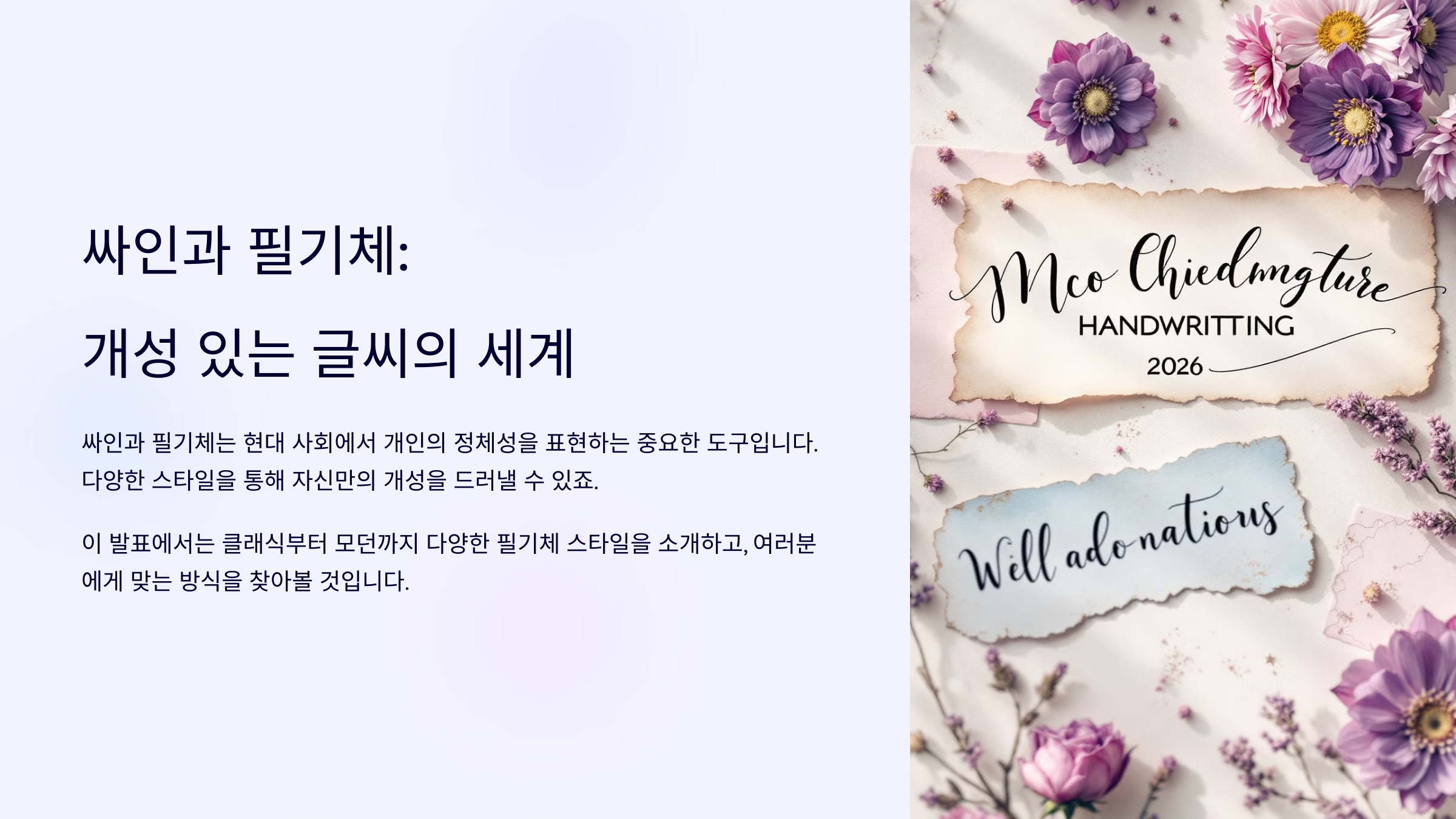
그렇다면, 싸인을 멋지게 보이게 하는 필기체에는 어떤 것들이 있을까요? 먼저, 싸인과 필기체의 관계부터 살펴볼게요! 🔍
싸인과 필기체의 관계 🖋️
싸인은 단순한 서명이 아니라 자신의 개성을 표현하는 중요한 요소예요. 특히 어떤 필기체를 선택하느냐에 따라 싸인의 느낌이 크게 달라질 수 있어요. ✍️
예를 들어, 곡선이 많고 부드러운 필기체는 우아하고 감성적인 느낌을 주고, 직선적이고 강한 필기체는 자신감과 카리스마를 강조할 수 있어요. 이처럼 필기체 하나로 싸인의 분위기가 완전히 달라질 수 있어요. 💡
📌 필기체 스타일별 싸인의 차이 🔍
필기체 스타일 특징 추천 대상 클래식한 필기체 우아하고 전통적인 느낌을 강조 고급스러운 이미지가 필요한 사람 모던한 필기체 깔끔하고 세련된 분위기 연출 비즈니스 및 공식 문서용 예술적인 필기체 곡선과 장식이 많아 독창적인 느낌 개성을 강조하고 싶은 사람 미니멀한 필기체 불필요한 요소를 제거한 심플한 스타일 깔끔한 서명을 원하는 사람 싸인 스타일을 정할 때는 자신의 이미지와 목적에 맞는 필기체를 선택하는 것이 중요해요. 그럼 먼저, 우아하고 고급스러운 클래식한 필기체 추천을 살펴볼까요? 🎩
클래식한 필기체 추천 🎩
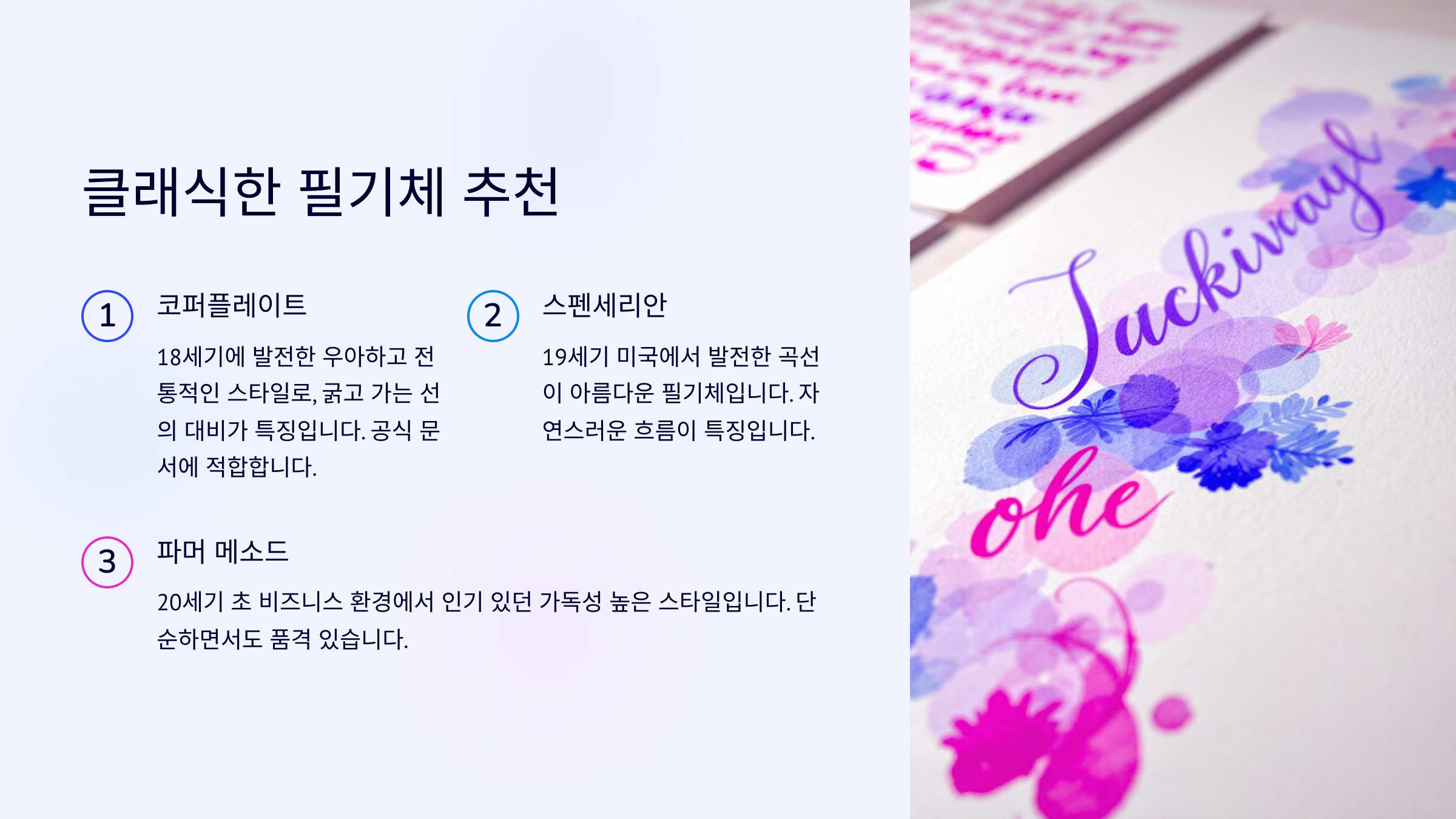
클래식한 필기체는 우아하고 고급스러운 분위기를 연출하는 데 적합해요. 특히 전통적인 싸인 스타일을 선호하는 분들에게 잘 어울려요. ✍️
고전적인 필기체는 곡선이 많고, 부드러우면서도 흐름이 자연스러운 것이 특징이에요. 예를 들어, 왕실 문서나 유명 예술가들의 서명에서 이런 스타일을 자주 볼 수 있죠. 💡
📌 클래식한 필기체 추천 ✅
필기체 특징 추천 대상 Spencerian Script 19세기 미국에서 유행한 우아한 필기체 전통적인 느낌을 원하는 분 Copperplate 곡선과 장식이 많아 귀족적인 분위기 우아한 싸인을 원한다면 Roundhand 유럽에서 발전한 부드러운 필기체 클래식하면서도 실용적인 싸인을 원할 때 Zanerian Script 예술적인 요소가 강한 고전 서체 고급스러운 스타일을 원할 때 클래식한 필기체는 전통적인 느낌과 우아함을 강조하는 데 최고예요! 그럼 이제 현대적이고 세련된 느낌을 주는 모던한 필기체도 살펴볼까요? ✨
모던하고 세련된 필기체 ✨
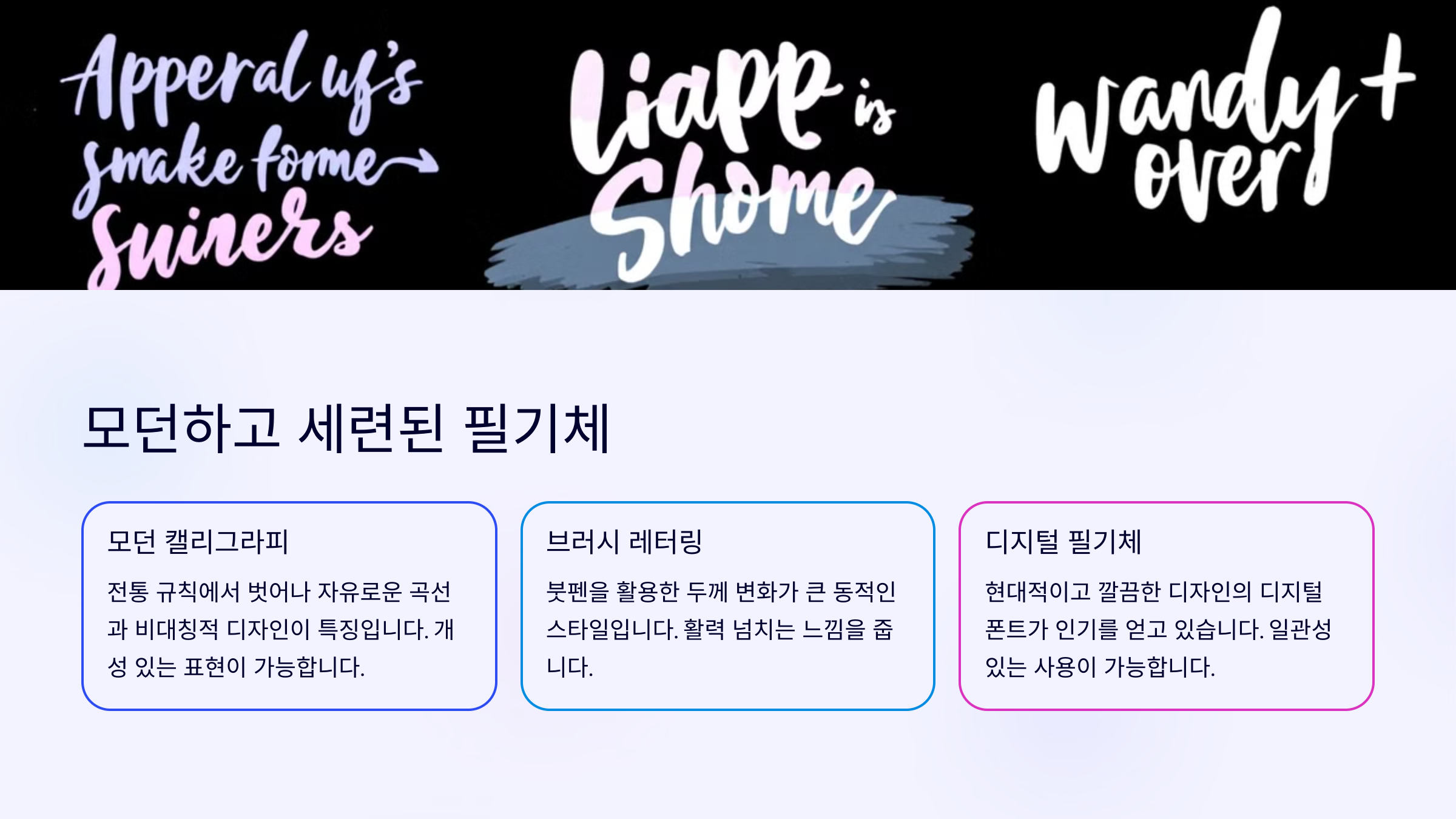
모던한 필기체는 깔끔하면서도 세련된 분위기를 연출하는 스타일이에요. 특히 비즈니스 서명, 공식 문서, 현대적인 감각의 싸인을 원할 때 적합해요. 🖋️
이런 스타일의 필기체는 획이 정리되어 있고, 불필요한 장식이 적으며, 가독성이 좋은 것이 특징이에요. 특히 CEO나 전문가들이 깔끔하고 믿음직한 이미지를 위해 선호하는 스타일이기도 해요. 💼
📌 모던한 필기체 추천 ✅
필기체 특징 추천 대상 Helvetica Script 단순하면서도 현대적인 필기체 비즈니스 및 전문직 종사자 Futura Handwritten 기하학적인 요소가 가미된 모던한 스타일 스타일리시한 싸인을 원하는 분 Monoline Script 균일한 굵기의 세련된 필기체 간결하면서도 감각적인 서명을 원할 때 Gotham Handwritten 깨끗하고 정돈된 느낌을 주는 필기체 깔끔하고 프로페셔널한 느낌을 원할 때 모던한 필기체는 전문적인 이미지와 세련된 감각을 강조하는 데 효과적이에요. 그럼 이제 예술적인 감각을 살릴 수 있는 필기체 스타일도 살펴볼까요? 🎨
예술적인 감각의 필기체 🎨
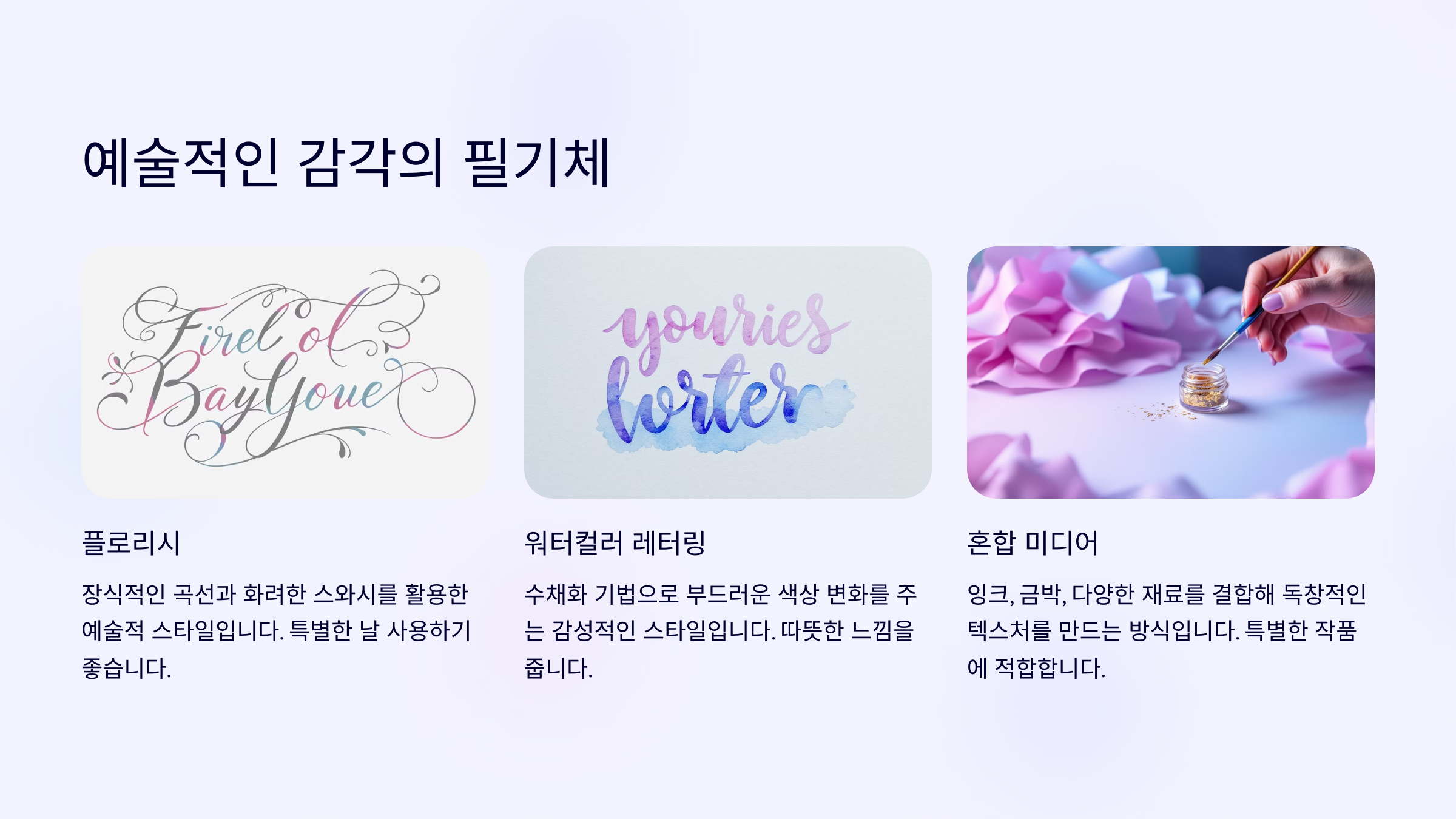
예술적인 필기체는 개성을 극대화하고 독창적인 분위기를 연출하는 스타일이에요. 특히 아티스트, 디자이너, 크리에이터처럼 창의적인 분야에서 활동하는 분들에게 어울리는 싸인 스타일이죠. 🖋️✨
이런 스타일의 필기체는 곡선이 많고 자유로운 형태를 가지며, 때로는 추상적인 느낌을 주기도 해요. 개성이 강한 싸인을 원한다면, 예술적인 필기체를 적극적으로 활용해 보세요! 🎭
📌 예술적인 필기체 추천 ✅
필기체 특징 추천 대상 Brush Script 붓글씨 느낌의 부드러운 필기체 아티스트, 일러스트레이터 Graffiti Style 스트리트 아트에서 영감을 받은 필기체 그래픽 디자이너, 크리에이터 Calligraphy Hand 고급스럽고 장식적인 캘리그래피 스타일 감성적인 싸인을 원할 때 Abstract Signature 획이 불규칙하고 개성이 강한 스타일 독창적인 싸인을 원할 때 예술적인 필기체는 자신만의 개성을 강조하고, 창의적인 느낌을 살리는 데 최적화된 스타일이에요! 그럼 이제 간결하면서도 멋진 필기체 스타일을 살펴볼까요? 🔍
간결하면서도 멋진 필기체 🔍
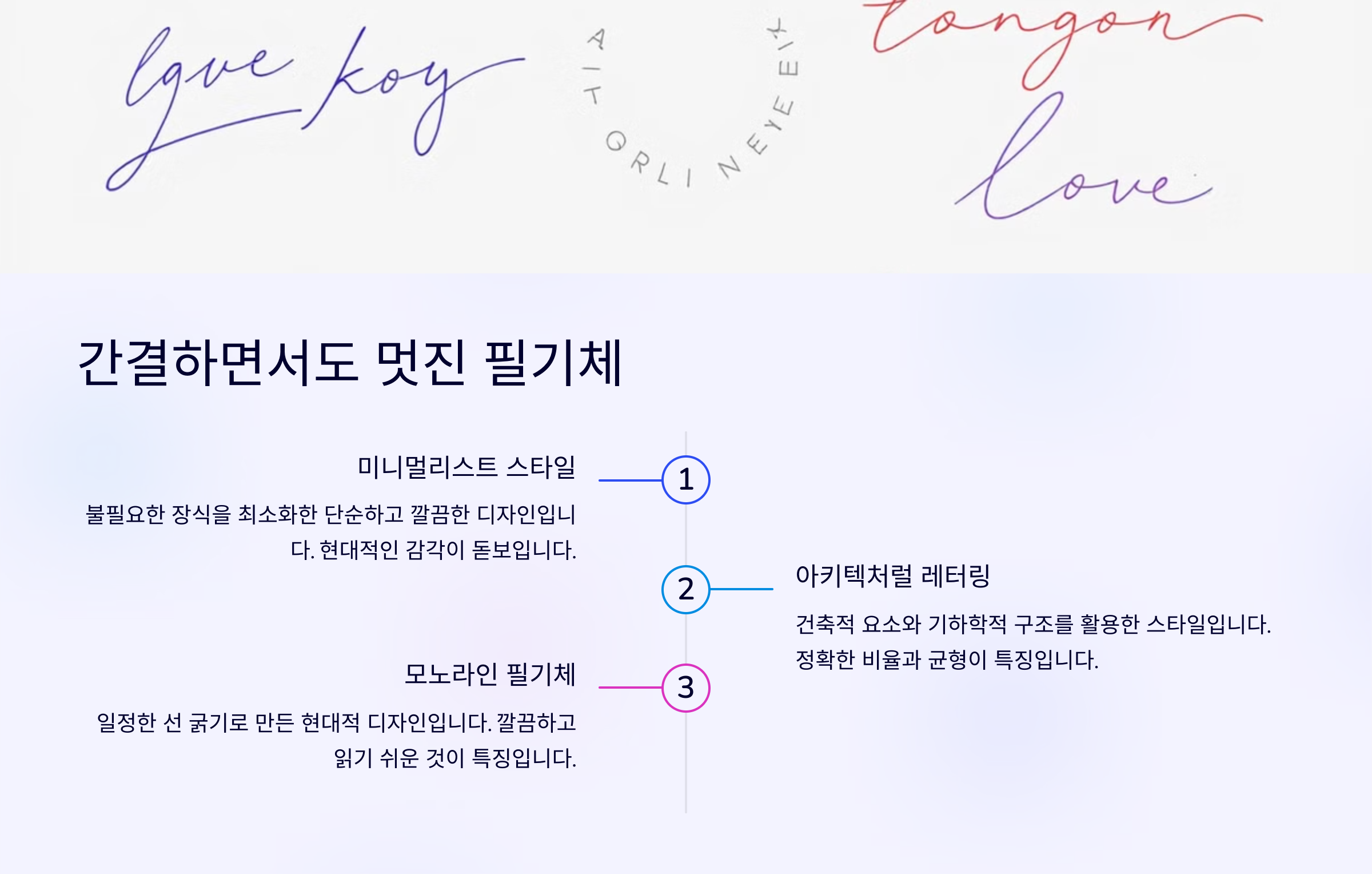
미니멀한 필기체는 불필요한 장식을 줄이고, 단순하면서도 세련된 느낌을 강조하는 스타일이에요. 특히 빠르고 간결한 싸인을 원하는 사람들에게 적합하죠. ✍️
이런 필기체는 획이 일정하고 균형감이 있으며, 가독성이 높은 것이 특징이에요. CEO나 실용적인 싸인을 선호하는 사람들은 이 스타일을 자주 선택해요. 💼
📌 간결하면서도 멋진 필기체 추천 ✅
필기체 특징 추천 대상 Monospace Script 획의 간격이 일정하고 균형이 잡힌 스타일 비즈니스 서명을 원하는 사람 Simple Handwriting 읽기 쉽고 자연스러운 손글씨 스타일 빠른 서명을 원하는 사람 Clean Line Script 곡선 없이 직선적인 요소가 많은 스타일 깔끔한 싸인을 원하는 사람 Minimal Sans 불필요한 장식 없이 단순한 느낌 최대한 심플한 서명을 원하는 사람 미니멀한 필기체는 시간이 지나도 변하지 않는 깔끔한 스타일을 원할 때 최적이에요! 그럼 이제 자신에게 맞는 필기체를 고르는 방법을 알아볼까요? 🔥
나에게 맞는 필기체 선택법 🔥
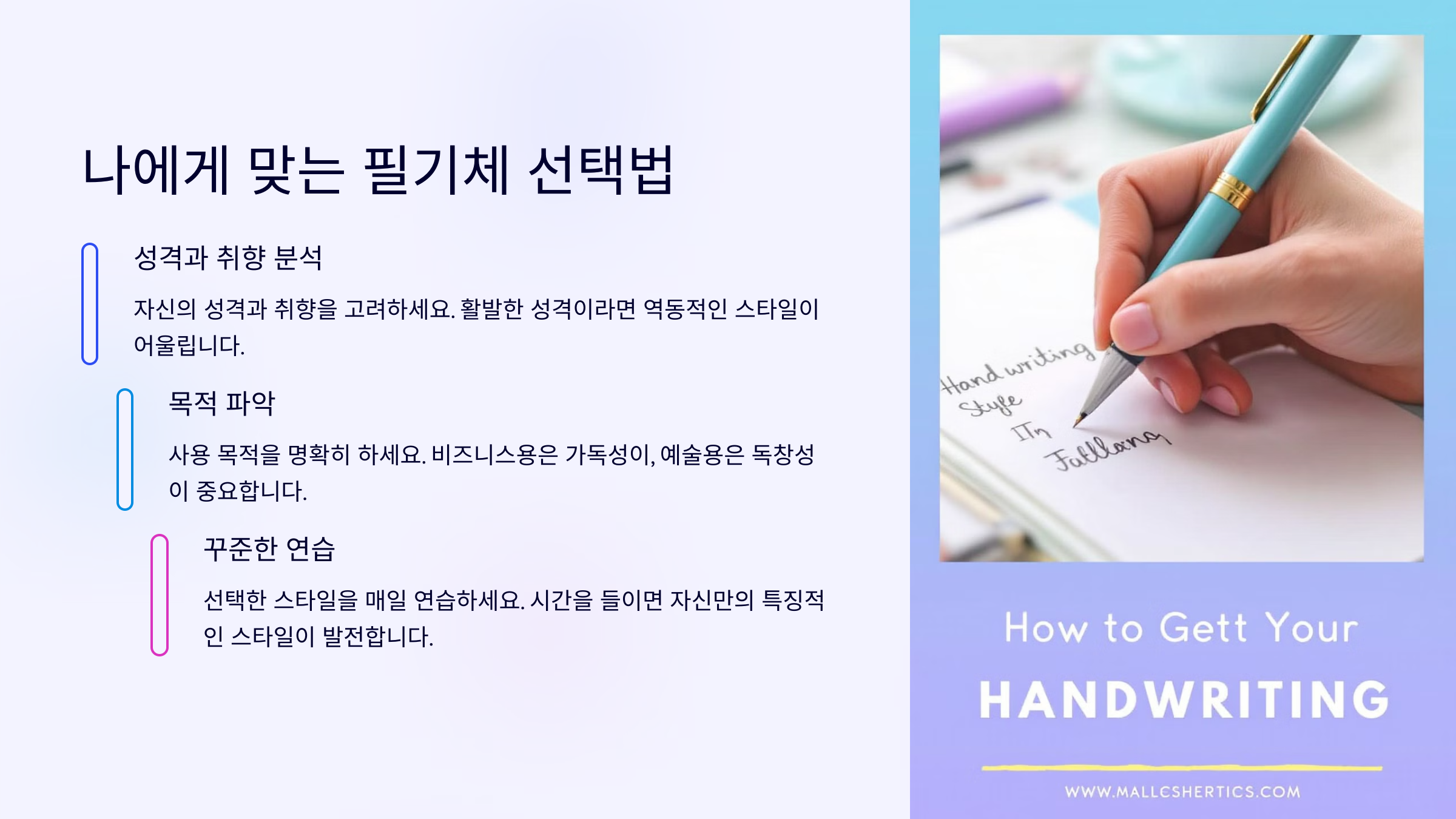
지금까지 다양한 스타일의 필기체를 살펴봤어요! ✍️ 이제 나에게 맞는 필기체를 어떻게 선택해야 할지 고민이 될 수 있어요. 그래서 싸인의 용도와 목적에 따라 필기체를 선택하는 방법을 정리해 봤어요. ✅
📌 나에게 맞는 필기체를 찾는 5단계 가이드 🧐
단계 설명 추천 스타일 1. 싸인의 용도 파악 비즈니스용인지, 개인 서명인지 목적을 정하기 모던한 필기체, 미니멀 스타일 2. 개성을 표현할지 고민 독창적인 느낌을 줄 것인지, 단순한 싸인을 원할 것인지 결정 예술적인 필기체, 클래식한 필기체 3. 가독성 고려 읽기 쉬운 싸인을 원한다면 글씨체가 정돈된 스타일 선택 모던한 필기체, 미니멀 스타일 4. 필기 속도와 편의성 자연스럽게 빠르게 쓸 수 있는지 테스트 간결한 필기체, 모던한 필기체 5. 자신만의 스타일 정하기 자신의 성격과 분위기를 반영한 스타일로 완성 본인의 취향에 맞게 선택 자신에게 맞는 필기체를 선택하면, 싸인의 개성이 더욱 돋보이고 자신만의 스타일을 완성할 수 있어요! 💯 마지막으로, 싸인과 필기체 관련 자주 묻는 질문(FAQ)을 정리해볼게요. 📢
FAQ
Q1. 필기체에 따라 싸인의 느낌이 정말 달라지나요?
A1. 네! 같은 이름이라도 필기체를 바꾸면 싸인의 분위기와 인상이 크게 달라질 수 있어요. ✍️
Q2. 가장 인기 있는 싸인용 필기체는 무엇인가요?
A2. Copperplate, Helvetica Script, Monospace Script 등이 싸인용 필기체로 많이 사용돼요. 🖋️
Q3. 빠른 싸인을 위해서는 어떤 필기체가 좋을까요?
A3. 간결하고 직선적인 필기체가 좋아요. 예를 들어, Simple Handwriting, Clean Line Script가 추천돼요. ⚡
Q4. 싸인에 예술적인 느낌을 더하고 싶다면?
A4. Brush Script, Graffiti Style, Calligraphy Hand 같은 예술적인 필기체를 선택하면 개성이 강한 싸인을 만들 수 있어요. 🎨
Q5. 싸인을 연습할 때 가장 중요한 요소는?
A5. 일관성을 유지하며 반복적으로 연습하는 것이 중요해요. 한 번 정한 스타일을 꾸준히 유지하면 손에 익게 돼요. 🖋️
Q6. 너무 복잡한 필기체를 쓰면 단점이 있나요?
A6. 네! 지나치게 복잡한 필기체는 가독성이 떨어지고, 빠르게 싸인하기 어려울 수 있어요. 실용성과 디자인의 균형을 맞추는 것이 중요해요. 🔍
Q7. 가독성과 개성을 모두 살릴 수 있는 필기체는?
A7. 모던한 필기체(Helvetica Script, Futura Handwritten)는 깔끔하면서도 스타일리시한 느낌을 동시에 줄 수 있어요. ✨
Q8. 싸인을 연습할 때 가장 좋은 방법은?
A8. 연필이나 펜을 사용해 반복 연습하고, 자신만의 리듬을 찾는 것이 중요해요. 꾸준히 연습하면 자연스럽고 멋진 싸인이 완성될 거예요! 🚀